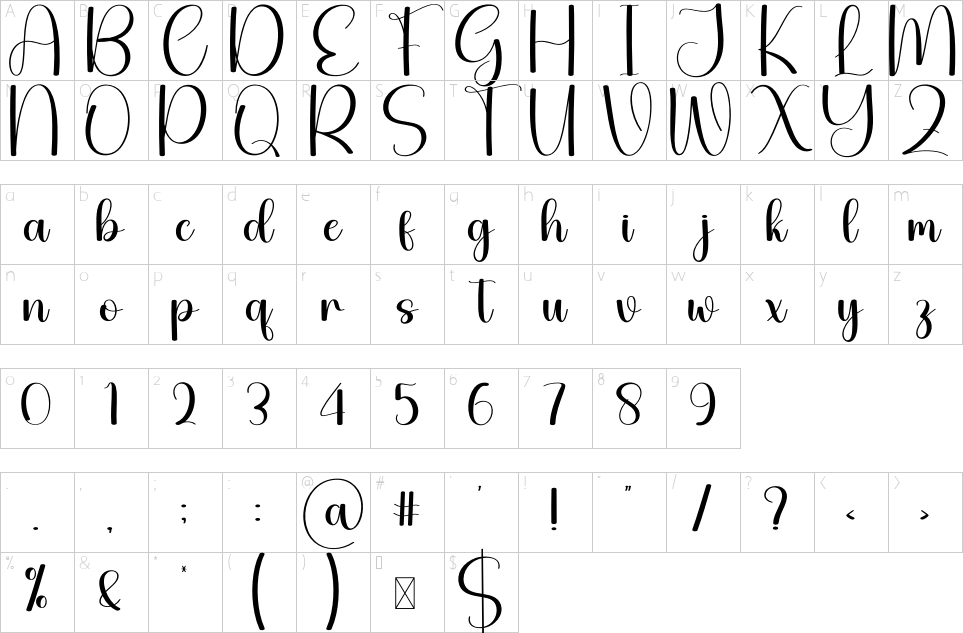
A fonte Justify oferece uma experiência visual única, perfeita para quem busca um equilíbrio entre elegância e simplicidade. Essa fonte grata foi projetada por scratchones e já foi baixada mais de 461 vezes, indicando seu valor e popularidade. Seja para personalizar efeitos em sites, desenvolver novas aplicações ou simplesmente adicionar um toque especial a seus designs, Justify proporciona uma variedade de opções para enriquecer suas criações. Se você está procurando por uma fonte que combine facilidade de uso com um design elegante, Justify é uma excelente escolha. Descubra por si mesmo os benefícios dessa fonte gratuita e descubra por que tantos designers já a aderiram a sua lista de fontes favoritas.